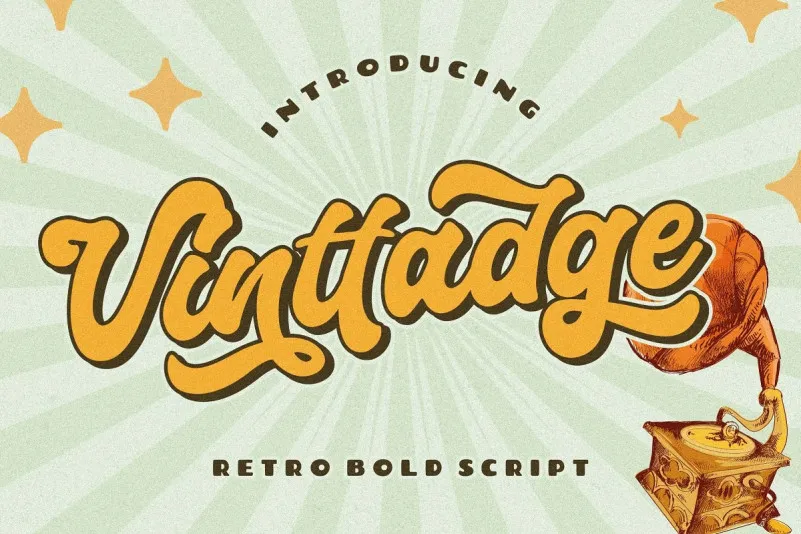
Vinttadge Font – Fonte Grátis
Vinttadge Font
Esta fonte é ideal para quem busca um equilíbrio perfeito entre modernidade e clareza. Ela destaca-se pela sua personalidade única e pelo contraste entre a força robusta e a delicadeza suave, criando uma imagem que se equipara ao design tipográfico dos anos 1930, conhecido como vintage ou vintee. Perfeita para diversos tipos de projetos, essa fonte é um choque de estilo perfeito para as suas criações. Ideal para trabalhos de marca, logos e designs de casamento, ela transmite uma sensação elegante e sofisticada sem deixar de ser contemporânea. É versátil o suficiente para combinar em aplicativos como posts no Instagram ou anúncios, em embalagens de produtos ou até mesmo nos desenhos de fotografias que você deseja destacar. Além disso, a fonte é perfeita para as invitações de festa e os materiais de escritório. Permite incorporá-la em qualquer projeto onde haja uma necessidade de transmitir uma atmosfera quase “escrita à mão”, proporcionando um toque delicado e único aos seus trabalhos.